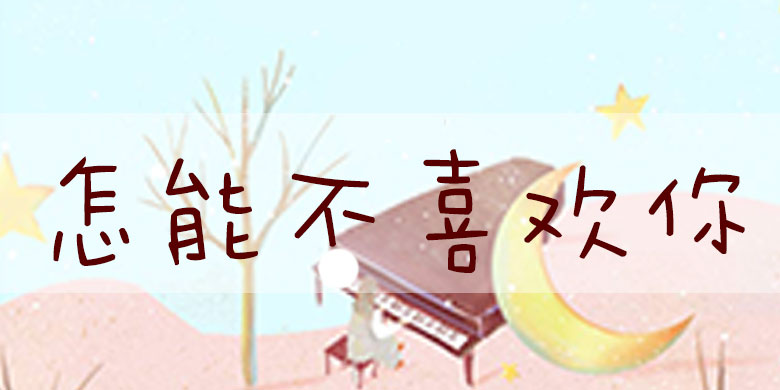
方正手迹-怎能不喜欢你
品牌:方正手迹设计师:刘晔发行时间:2019字库编码:大陆简体(GB2312-80)分类:创意书写字体属性:精品字
方正手迹-怎能不喜欢你
怎能不喜欢你是一款具有青春活力、少女气息、又带点青涩的字体。它像花季的少女,时而欢声笑语,时而任性安静。适用于少儿类书刊,及现代诗歌、短文的排版以及文化、商业类品牌的广告语设计。